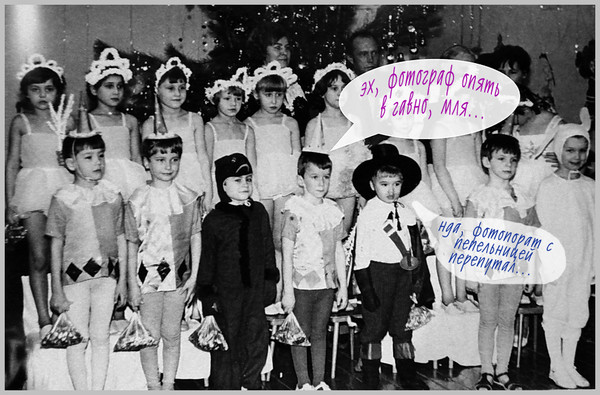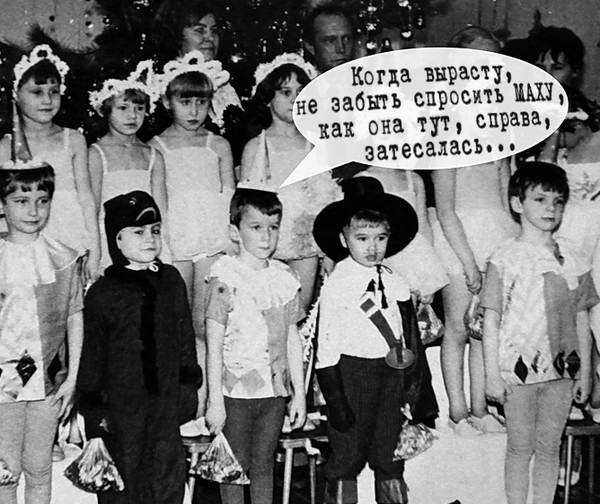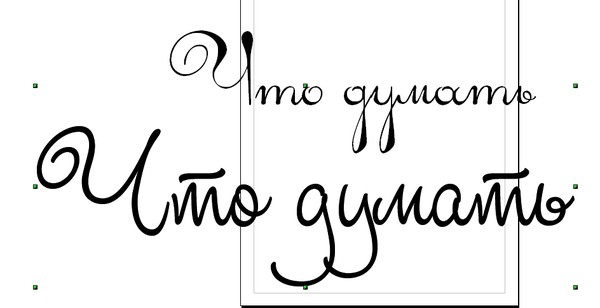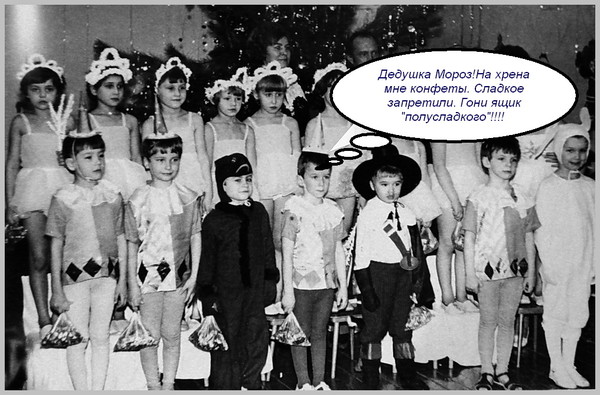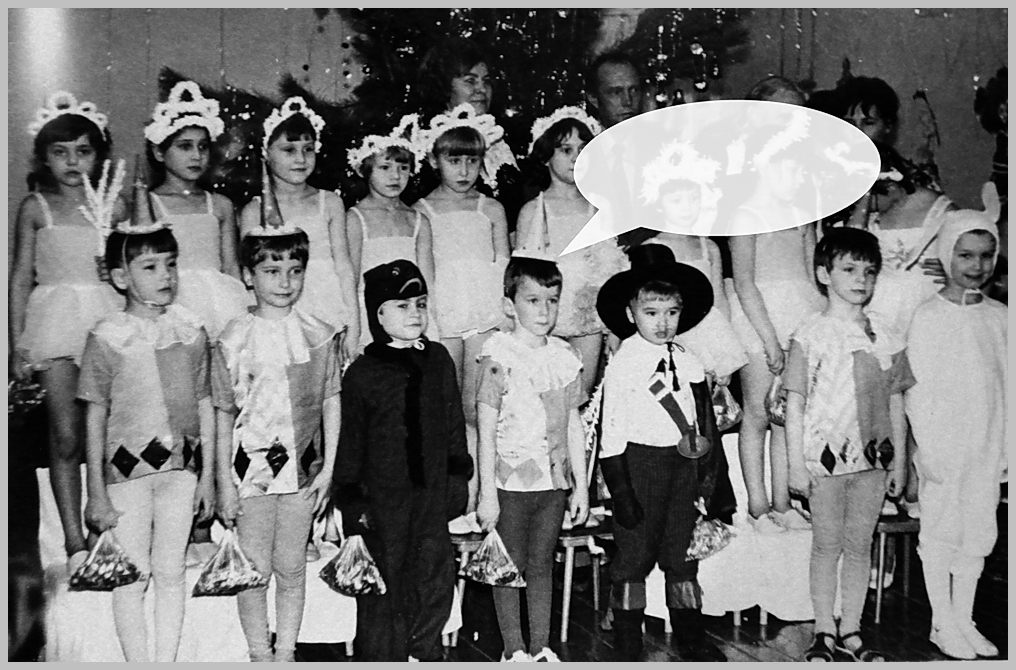
Какой шрифт лучше всего подойдёт к этой фотографии?
Пытаюсь что-то к водяриному конкурсу прЫдумать. Пока просто разминаю моцк.
На этой фоте зачепятлён мой организм в детском саду. Что он думает, как вы щщитаете? :))
Не знаю ЧТО думает этот организм, но думает он шрифтом Comic Sans... наверняка! :)
Чодураа Митей Думать шрифтом - это окуенчик! Покупаю! :)))
Адвер Готика - только сделать большой и границы размыть и при наложении в тенях придать волшебства
Чодураа Митей Ну пример покажи, не жадничай.
а конфет то скока))))))))))))) )
Чодураа Митей "а конфет-то скока мало!!!"
В тему. :)
"да когда же разрешат есть конфеты?! "
;-))) Угадал?
Чодураа Митей "да когда же этот фатограф свалит?!" :))
Мне нравится шрифт Comic Sans MS
"Фотограф - лопух!! ! Ну кто так снимает? ! Дефчонок надо вперед ставить - они красивые!! "
Чодураа Митей Не-е... Этот шрифт из прошлого века. :(
Я всё правильно сделал . да точно - Я всё правильно сделал.. . без сомнений я всё правильно сделал = отпусите уже.. . конфеты хочу !!!
Чодураа Митей Одобрям! :)
"когда выросту.... точно, стану Мойшей"
Чодураа Митей Как в воду глядишь! :))
Похоже этот черный пингвин у меня конфет отсыпал.. .
....тоже шута нашли мать твою....
Чодураа Митей Шо, Новый Год - не праздник?
Чодураа Митей "...сухое без запивона уже не лезет..." :)
Шрифт не знаю... какой.
Но подлянку явно задумал:))))))
Чодураа Митей Гнусная инсинуация!!
До* блись. . дитя стишОк рассказывает ..
В лесу родилась Ёлочка
А рядом с нею пень!
и пень просил у ёлочки .. -ЧЕТЫРЕ раза в день. .
и Ёлочка ответила ..
Иди ты наКуй пень ..
Когда пойду на пенЗи ю? би хоть целый день!
Чодураа Митей Ты чо! Я тогда ишшо очень культурно матерился. :)))
Наверняка то что нарисовано и думает.
Чодураа Митей "Овальчика бы щас...." Угу?
Может, TaddyBear, AriadnaScript, а может, BetinaScript и похожие
Чодураа Митей Прикольные шрифты! Пасиба! :)
все конфеты и мандарины я сожру сам....
Чодураа Митей Здравствуй, диатез! :)
хм, вроде еще и корпоративное угощение в подарочном полиэтилене, а половина мужского коллектива - без штанов)) )
шрифт - любой, читабельный, желательно русский.
а хотите Вы, Милейший Мойша, домой поскорее - конфеты кушать... )
Шрифт Propisi...
Он думает "... надо будет Закладную настрочить.... "
Чодураа Митей Андрей, ну ведь подразмыть нада же було шрифток! :)))
такой сойдет?
Чодураа Митей Нуачо! Тоже вариянт! :))
Шрифт Aple
Чодураа Митей Не знаю такого. Мне стыдно. :(